Font chữ 30/4 1/5 Việt hóa đẹp, ấn tượng, miễn phí
Font chữ 30/4 giúp thiết kế banner, poster và các ấn phẩm kỷ niệm Ngày Giải phóng miền Nam trở nên ấn tượng hơn. Những kiểu chữ mang phong cách lịch sử, mạnh mẽ và trang trọng sẽ thể hiện tinh thần hào hùng của dân tộc. Cùng khám phá các font chữ đẹp, miễn phí và phù hợp nhất cho dịp 30/4!
Tổng hợp font chữ 30/4 1/5 độc đáo, hòa quyện tinh thần tự hào dân tộc và không khí lễ hội.
Lấy cảm hứng từ diện mạo Sài Gòn trước 1975, bộ font Hồi ức Sài Gòn của Iciel được Việt hóa tinh tế. Mỗi font là một lát cắt ký ức, tái hiện chân thật các kiểu chữ in trên báo chí xưa.
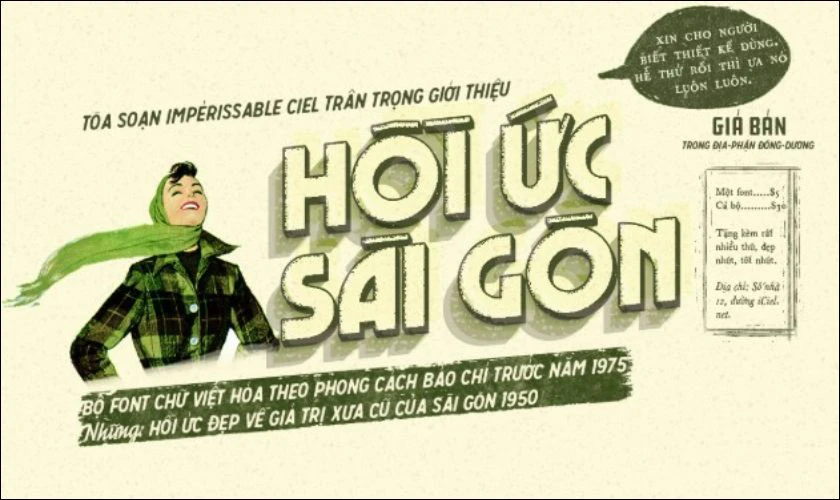
Tác giả đã dày công nghiên cứu tư liệu cũ, chăm chút đến từng dấu câu. Để mang về một bộ sưu tập mang đậm không khí của một Sài Gòn đầy kỷ niệm.
Giá trị xưa cũ là bộ font mang đậm tinh thần của thời kỳ bao cấp. Được phát triển bởi iCiel, phông chữ này không chỉ Việt hóa mà còn thể hiện rõ dấu ấn của cách đặt dấu xưa.
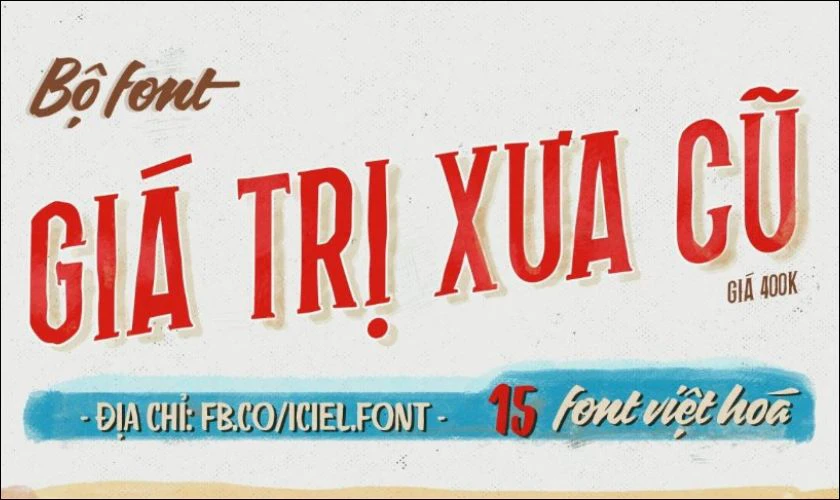
Với thiết kế tỉ mỉ kéo dài suốt gần 2 tháng, bộ font là lựa chọn lý tưởng cho các thiết kế mang màu sắc retro, vintage và quảng cáo xưa.
Font Classique Saigon do nhà thiết kế Mạnh Nguyễn sáng tạo. Nổi bật với phong cách đặc trưng của những năm 50-60 tại Sài Gòn. Nổi danh sau khi xuất hiện trong bộ phim “Cô Ba Sài Gòn”.
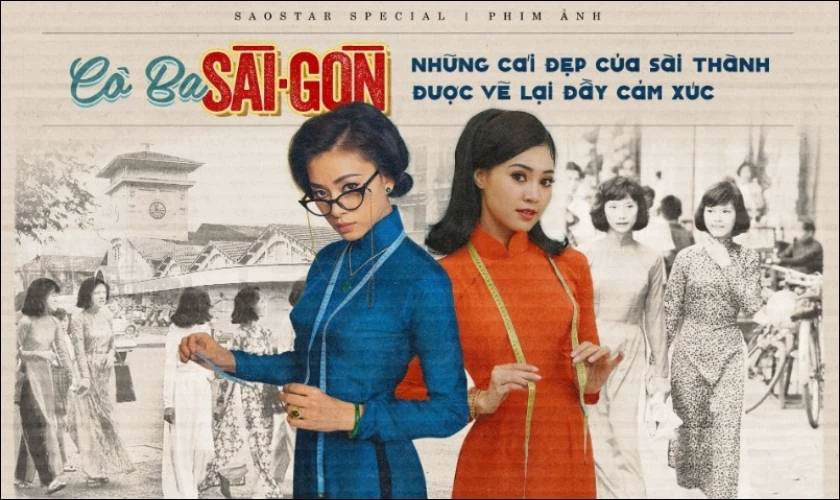
Đây là một font chữ không chỉ đẹp mà còn kể lại một câu chuyện văn hóa sống động qua từng nét bút.
Bộ font Xưa cũ là tập hợp kiểu chữ được tuyển chọn bởi anh Lê Tuấn Anh. Với cảm hứng từ những bảng hiệu cũ kỹ của Việt Nam thập niên trước.
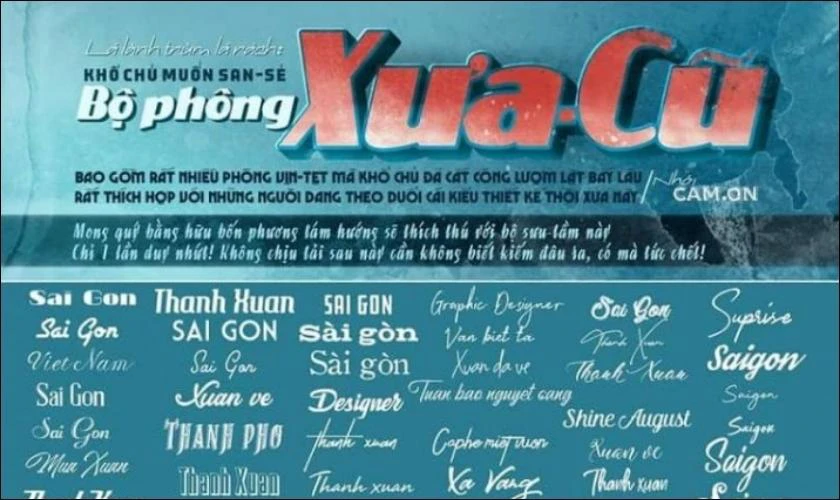
Từng phông mang đậm tinh thần hoài niệm, tái hiện vẻ đẹp mộc mạc, gần gũi. Một bộ sưu tập lý tưởng cho các nhà thiết kế theo đuổi phong cách cổ điển.
Lấy cảm hứng từ các bìa sách và banner quảng cáo cũ của Việt Nam những năm 1980. Font chữ Bìa sách xưa là sản phẩm tâm huyết của tác giả Tống Văn Hiệp.
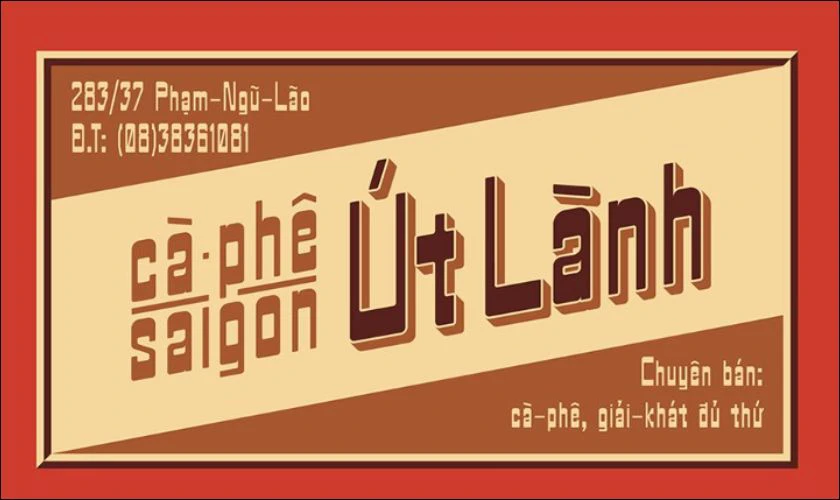
Điểm đặc trưng nằm ở kiểu chữ với nét ngang đậm và nét đứng thanh mảnh - vừa cổ điển vừa cá tính.
MTD Yessy là font viết tay mang phong cách retro đang khá hot trong 2026. Các nét chữ mềm mại, hơi nghiêng tạo cảm giác như chữ viết trong thư tay hoặc poster phim xưa.
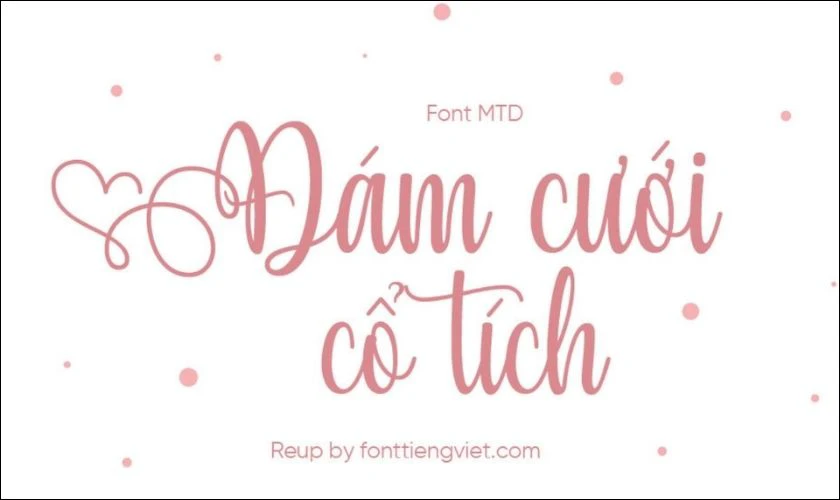
Font này rất hợp để làm caption, tiêu đề phụ hoặc nội dung mang tính cảm xúc. Khi dùng trong thiết kế 30/4, nó giúp tổng thể trở nên gần gũi và có chiều sâu hơn.
MJ Bygonest lấy cảm hứng từ thời kỳ bao cấp với kiểu chữ block dày, vuông vức. Nhìn vào là thấy ngay vibe poster cổ động hoặc tem phiếu ngày xưa.
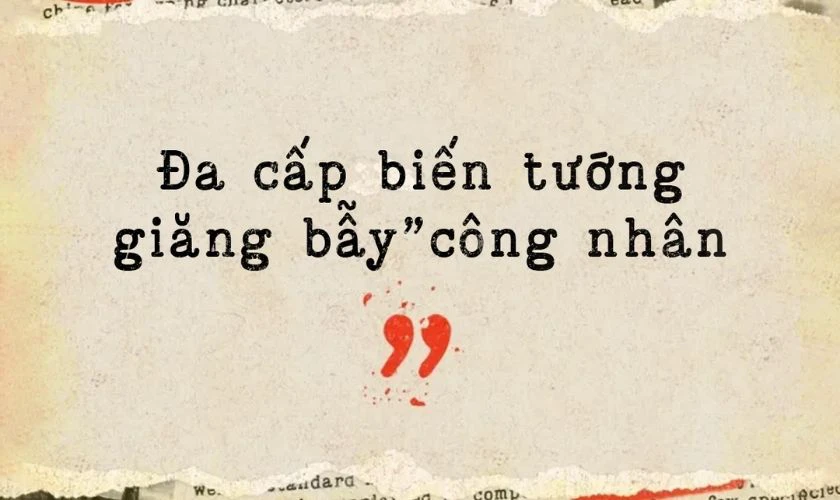
Font này cực kỳ hợp cho tiêu đề lớn, slogan hoặc banner 30/4. Nếu bạn muốn tạo cảm giác “lịch sử - khí thế”, đây là lựa chọn rất đáng dùng.
DFVN TAN - SALTERS là font display mang phong cách vintage pha hiện đại. Các đường nét được xử lý tinh tế, tạo cảm giác cao cấp và khác biệt so với font retro thông thường.
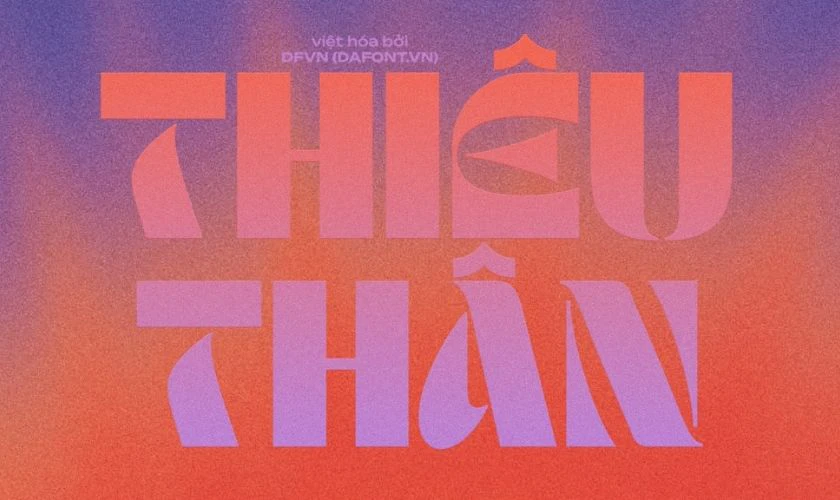
Font này phù hợp cho các thiết kế 30/4 mang hướng editorial, poster nghệ thuật hoặc branding. Dùng cho tiêu đề sẽ tạo điểm nhấn rất mạnh.
Nhóm font Groovy 70s (retro disco) đang quay lại mạnh trong thiết kế 2026. Chữ bo tròn, uốn lượn và rất “vui mắt”, tạo cảm giác năng động, trẻ trung.
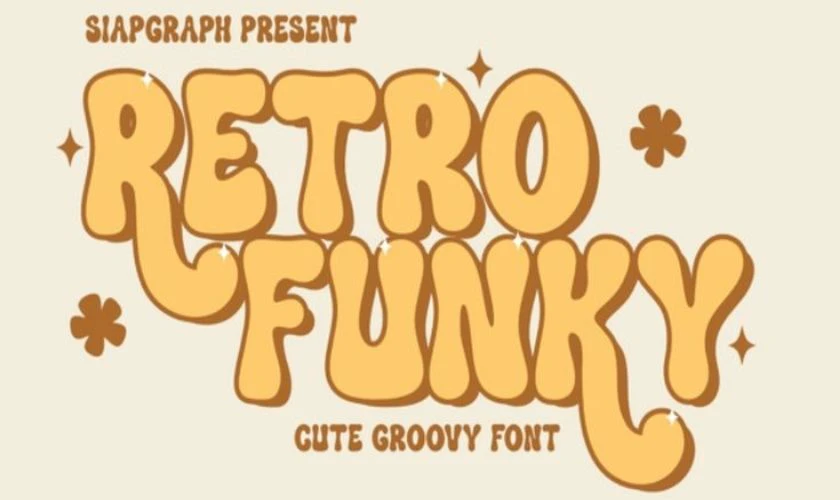
Bạn có thể dùng font này cho các bài đăng mạng xã hội, banner hoặc nội dung sáng tạo về ngày 30/4. Với các chữ uốn lượn, bo tròn đầy màu sắc, thiết kế của bạn sẽ trở nên nổi bật, thu hút ánh nhìn nhưng vẫn giữ được sự thân thiện và vui nhộn, không hề nặng nề hay nghiêm túc.
DFVN Lacquer là font dạng brush với hiệu ứng “chảy sơn”, tạo cảm giác rất sống động và có năng lượng. Các nét chữ dày, dứt khoát giúp tăng độ nổi bật cho thiết kế.
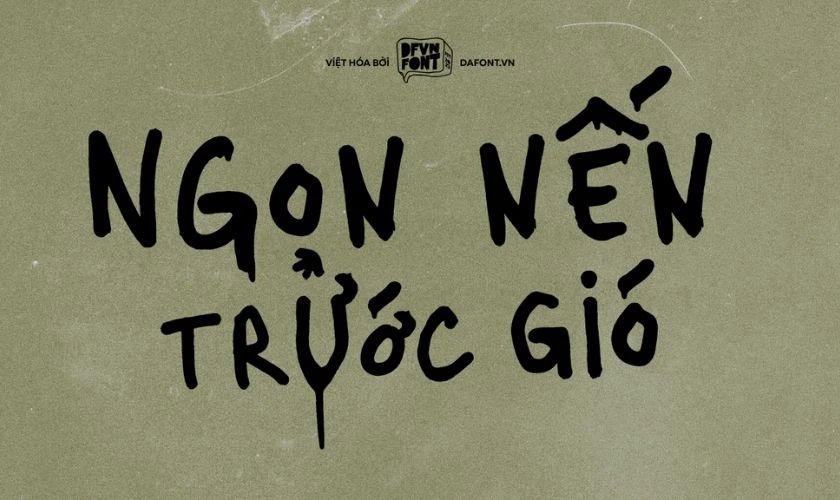
Font này phù hợp cho tiêu đề, khẩu hiệu hoặc highlight nội dung. Khi dùng trong thiết kế 30/4, nó mang lại cảm giác mạnh mẽ và đầy cảm xúc.
Hãy cùng khám phá bộ font chữ 30/4 1/5 Việt hóa miễn phí, đẹp mắt và độc đáo. Được thiết kế đặc biệt để tôn vinh tinh thần đoàn kết và tự hào dân tộc. Tham khảo ngay để sử dụng cho các dự án sáng tạo của bạn!
MJ Paztime là một font chữ mang phong cách cổ điển xen lẫn hiện đại. Font chữ phù hợp với các thiết kế mang hơi hướng hoài niệm nhưng vẫn toát lên sự tinh tế.
Phiên bản Việt hóa giữ nguyên độ mềm mại và nét sang trọng vốn có của font gốc.
NVN Cocogoose Vintage là font mang đậm chất retro với các đường nét mạnh mẽ, dứt khoát. Font thích hợp cho các thiết kế poster, logo hoặc tiêu đề cần tạo điểm nhấn ấn tượng.
Phiên bản Việt hóa đầy đủ dấu tiếng Việt, giữ nguyên chất “vintage” đặc trưng.
UTM Gunslinger mang đến phong cách viễn Tây đậm chất cao bồi với các đường nét góc cạnh và phá cách.
Font rất phù hợp với các thiết kế mang phong cách retro Mỹ, đây là thiết kế độc đáo cho sự kiện.
UTM Euphoria là một font mang đậm tính nghệ thuật, đường nét bay bổng, uyển chuyển. Phù hợp với các thiết kế lãng mạn, trang trí, thiệp cưới hay các sản phẩm handmade.